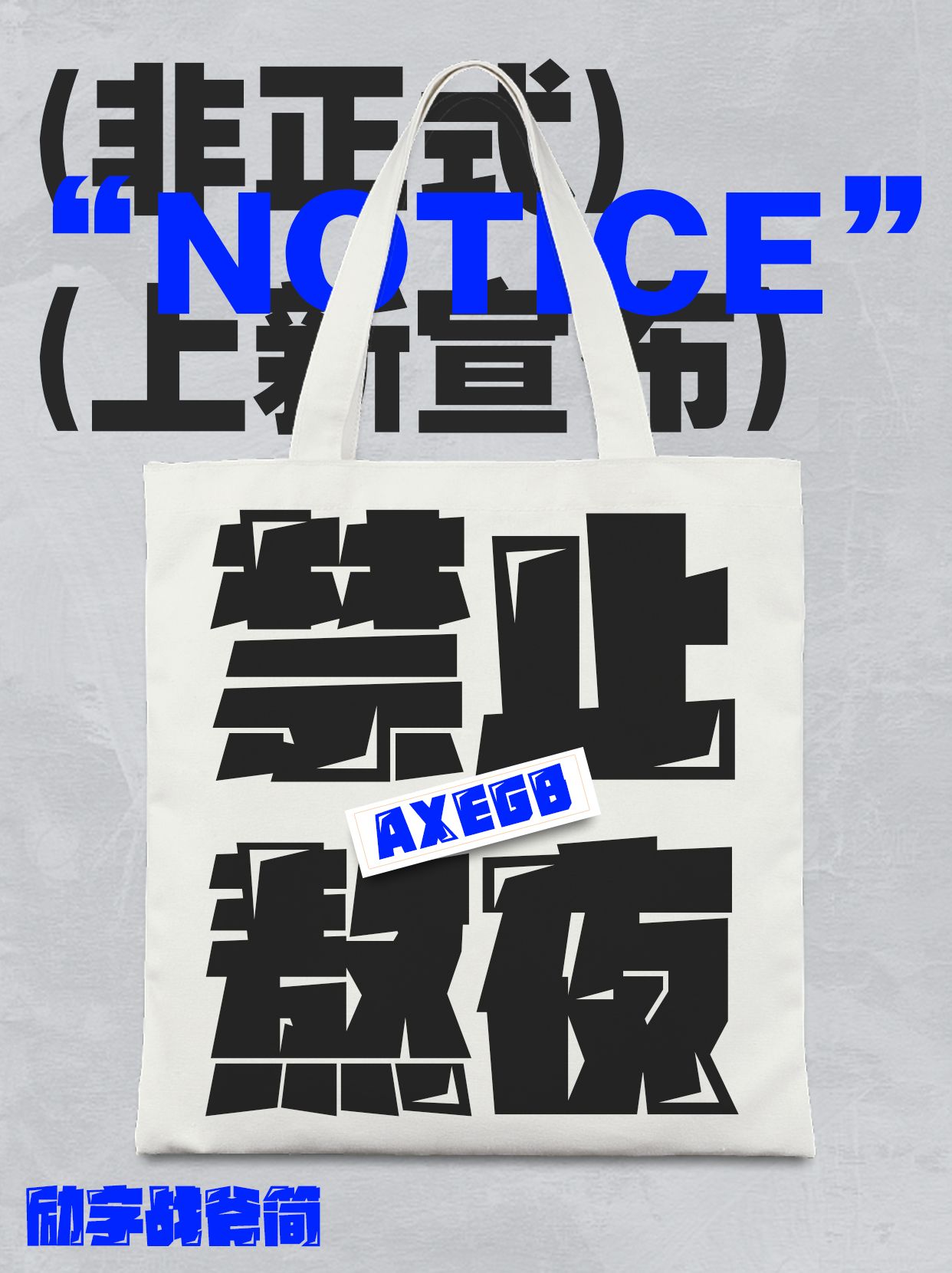
《乘风2023》在盛夏告别,《披荆斩棘3》在夏末回归,节目组一次性官宣了32位嘉宾,新一轮的披哥竞技即将揭开,内娱观众,总算又有团综舞台可追。励字造梦共创字库精选2款综艺字体,助力《披荆斩棘》的舞台。
励字战斧简 超级黑适合资历、咖位够大,也有很强的路人缘、综艺的活跃率非常高的哥哥。
该字体是一款现代创意型黑体,字型厚重略带一些开放性。笔画粗细做不均等形状,横竖笔画呈梯形分布,借用现代黑体主骨架进行创意性发挥,撇、捺、点加入更多梯形元素,整体风格偏硬,左上和右下加了对角高光,让风格更加强烈且突出,大标题字的特征明显,具有强烈的现代文艺特征。
励字暴风简 超级黑适合老牌男神,有情怀加成,自带回忆杀滤镜。
该字体是一款现代创意型黑体,字型厚重略带一些开放性。笔画粗细做不均等形状,横竖笔画呈梯形分布,借用现代黑体主骨架进行创意性发挥,撇、捺、点加入更多梯形元素,整体风格偏硬,横竖笔划的不规则感打破了传统的认知,具有强烈的现代文艺特征。